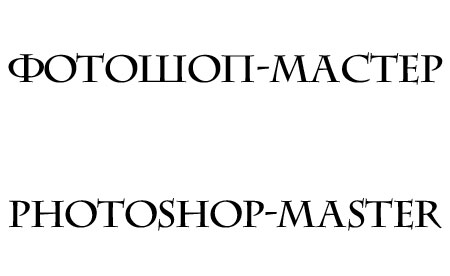
arinaheart, большими буквами пишет потому что в оригинальном, официальном шрифте у которого нет официальной поддержки кириллицы тоже все буквы заглавные а точнее прописные, даже там где должны быть строчные буквы а кириллицу делали по аналогии оригинального шрифта. Так кириллицу делают во многих шрифтах. Если есть в латинице шрифта строчные буквы, кириллизаторы добавляют строчные буквы, нет в латинице строчных букв и там только прописные, кириллизаторы добавляют только прописные буквы. Вот и вся арифметика! =)
ШРИФТ КРАСИВЫЙ НО ПОЧЕМУ ОН НЕ ПИШЕТ маленькими буквами?
arinaheart, большими буквами пишет потому что в оригинальном, официальном шрифте у которого нет официальной поддержки кириллицы тоже все буквы заглавные а точнее прописные, даже там где должны быть строчные буквы а кириллицу делали по аналогии оригинального шрифта. Так кириллицу делают во многих шрифтах. Если есть в латинице шрифта строчные буквы, кириллизаторы добавляют строчные буквы, нет в латинице строчных букв и там только прописные, кириллизаторы добавляют только прописные буквы. Вот и вся арифметика! =)
Нормально всё с кириллицей и везде отображается отлично!
Написано с поддержкой русского языка... а на деле... без...
не та категория. русский не поддерживает
ОДИН ИЗ ЛУЧШИХ